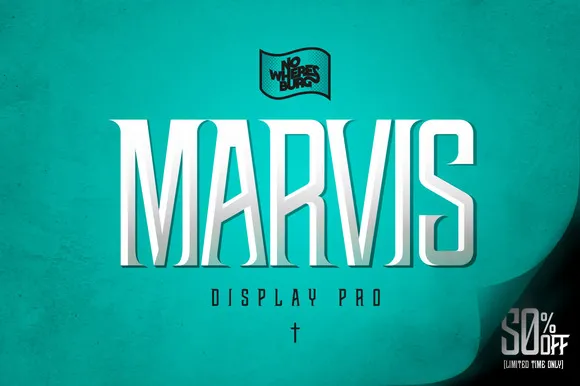
A NWB Marvis Display Pro é uma fonte display moderna inspirada nas elegantes tipografias vintage do final do século XIX. As linhas curvas e suaves dessa fonte oferecem um toque sofisticado para aplicações de design gráfico, especialmente em elementos como subtítulos de cartazes, títulos de filmes, rótulos de produtos, identidades de marcas e qualquer outra coisa que você possa imaginar. Com mais de 290 ligaturas e um total de cerca de 1357 gírias, essa fonte oferece opções incríveis para a personalização de tipos em posters, filmes e rótulos de produtos. Além disso, ela permite alternativas contextualmente sensíveis e 35+ catchwords que dão mais flexibilidade ao designer. NWB Marvis Display Pro é perfeita tanto para aplicações tradicionais quanto para modernas necessidades de design visual.